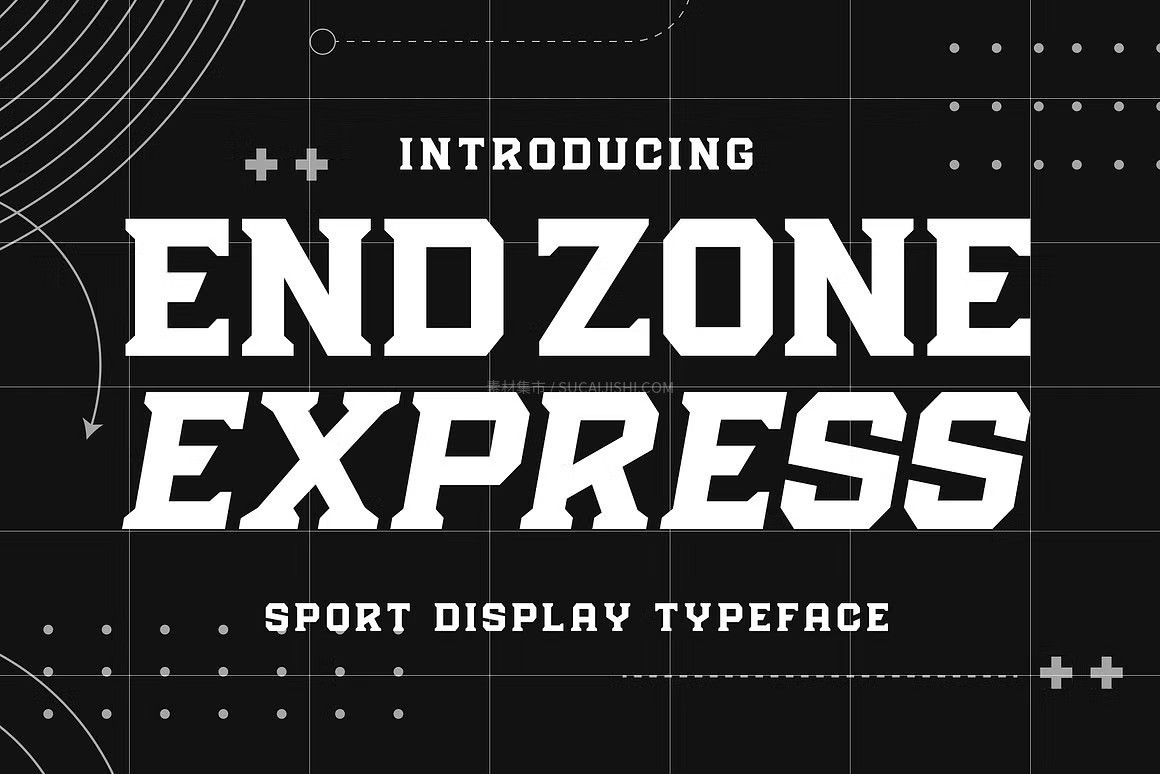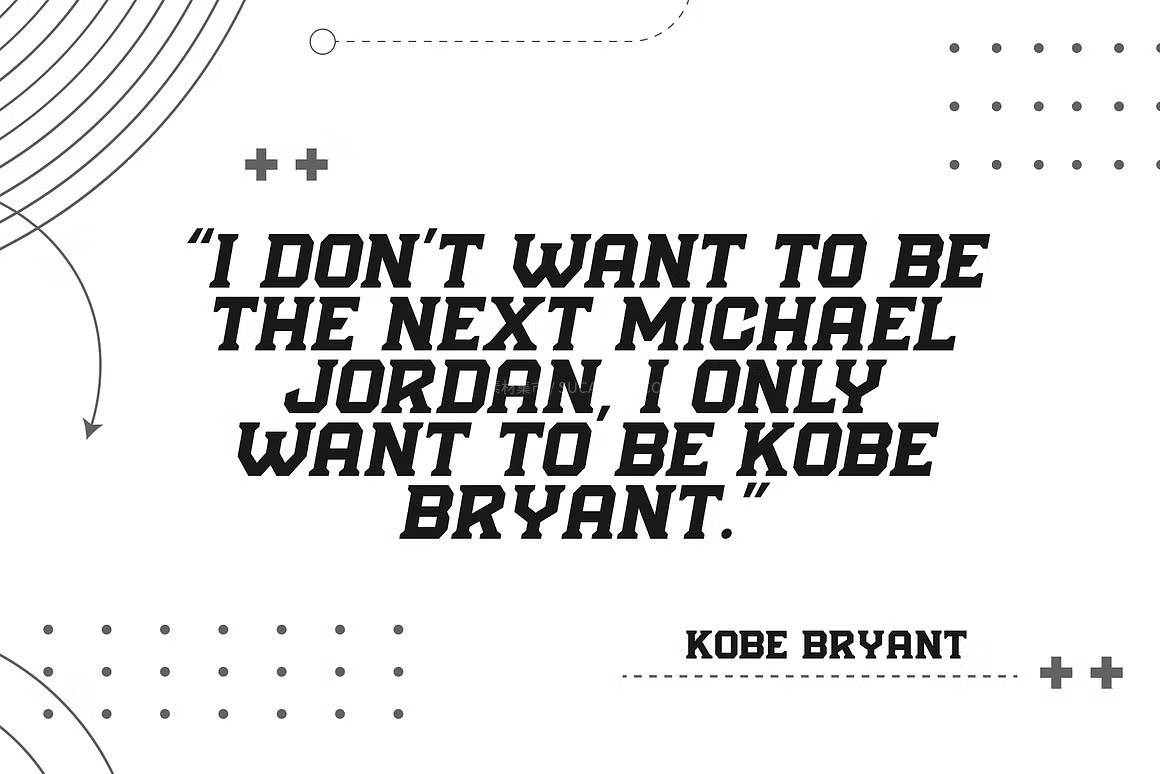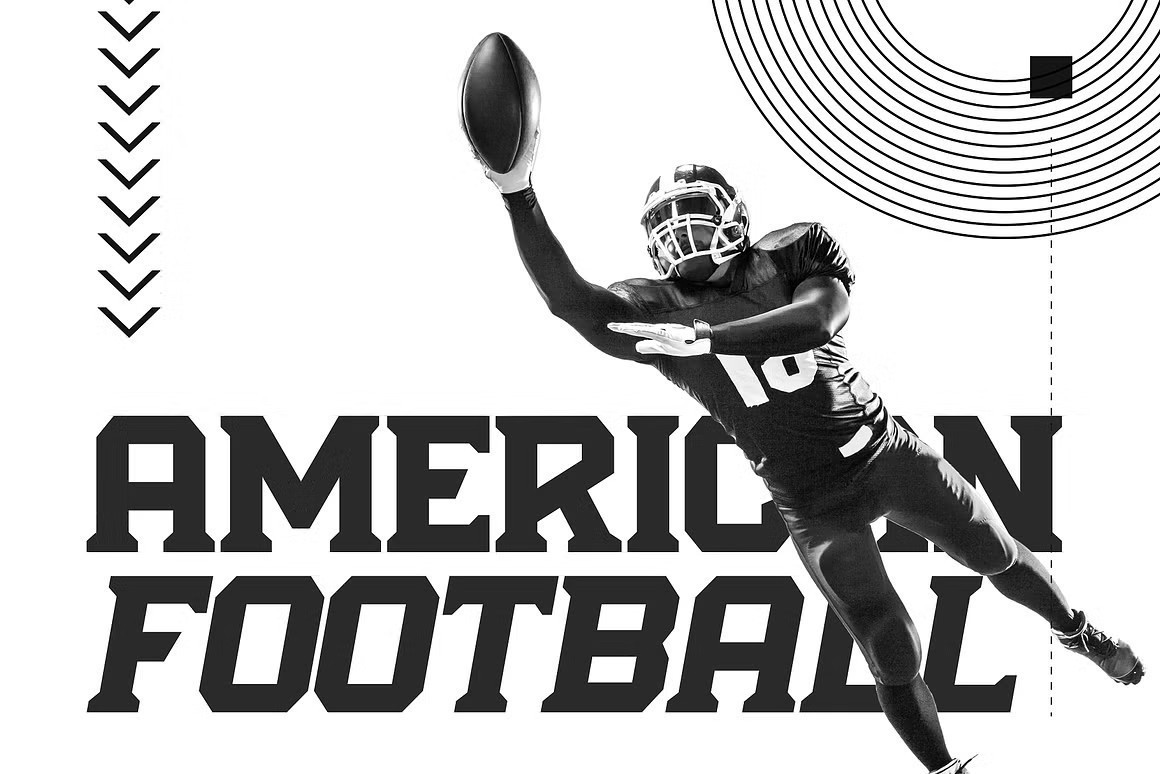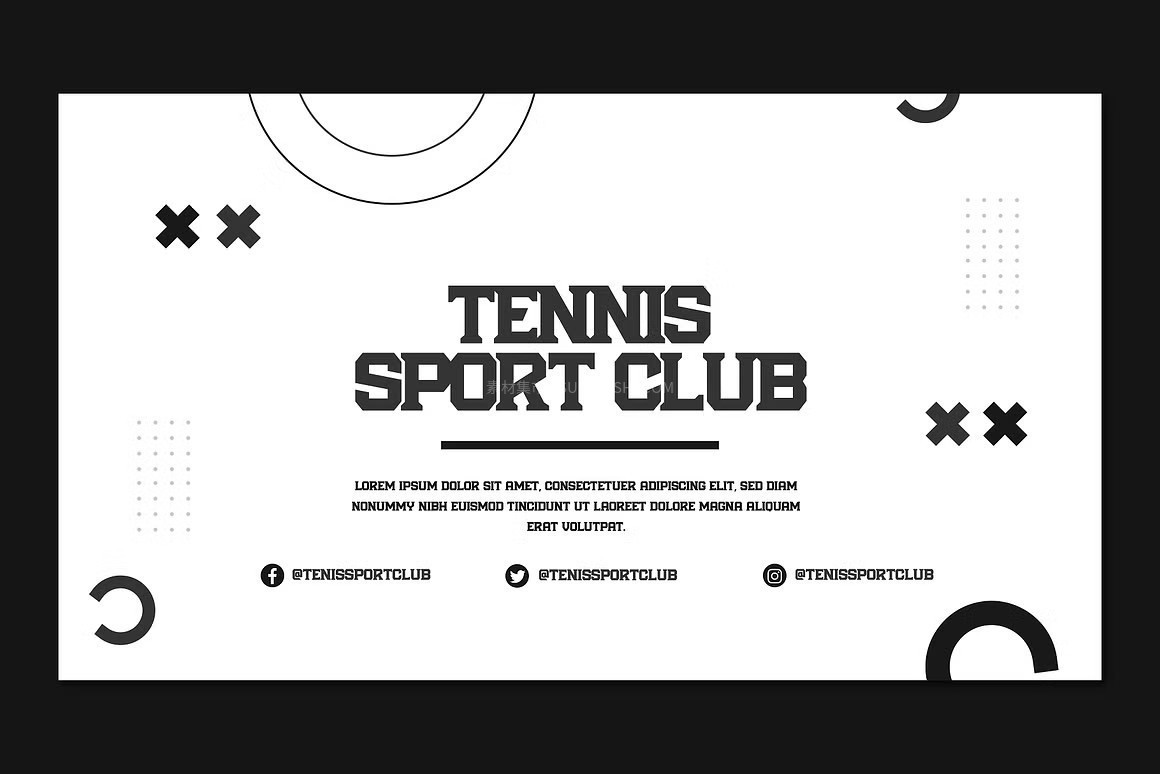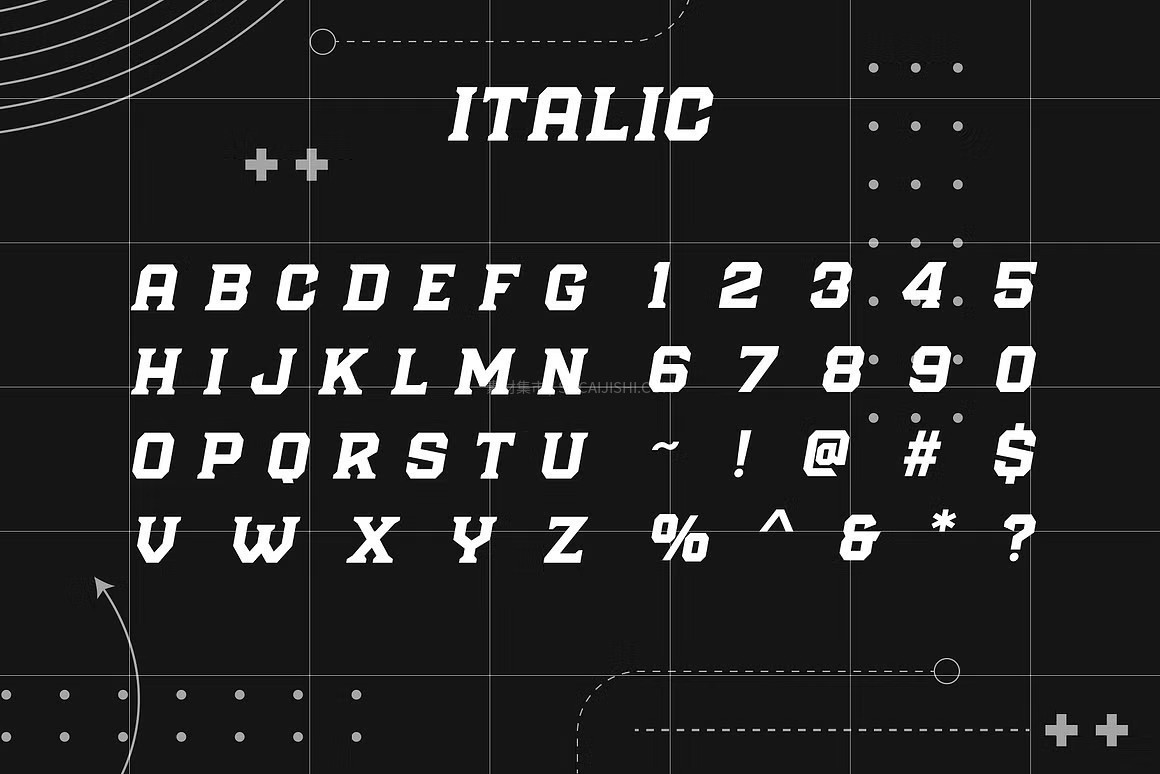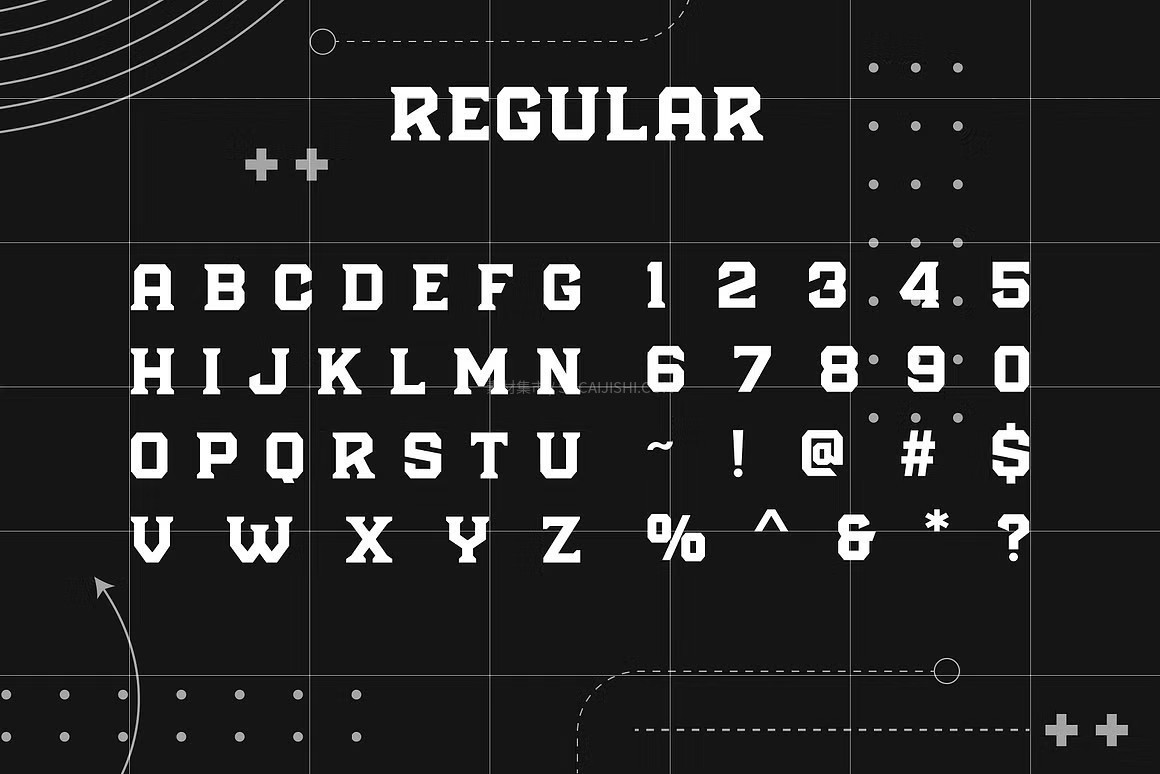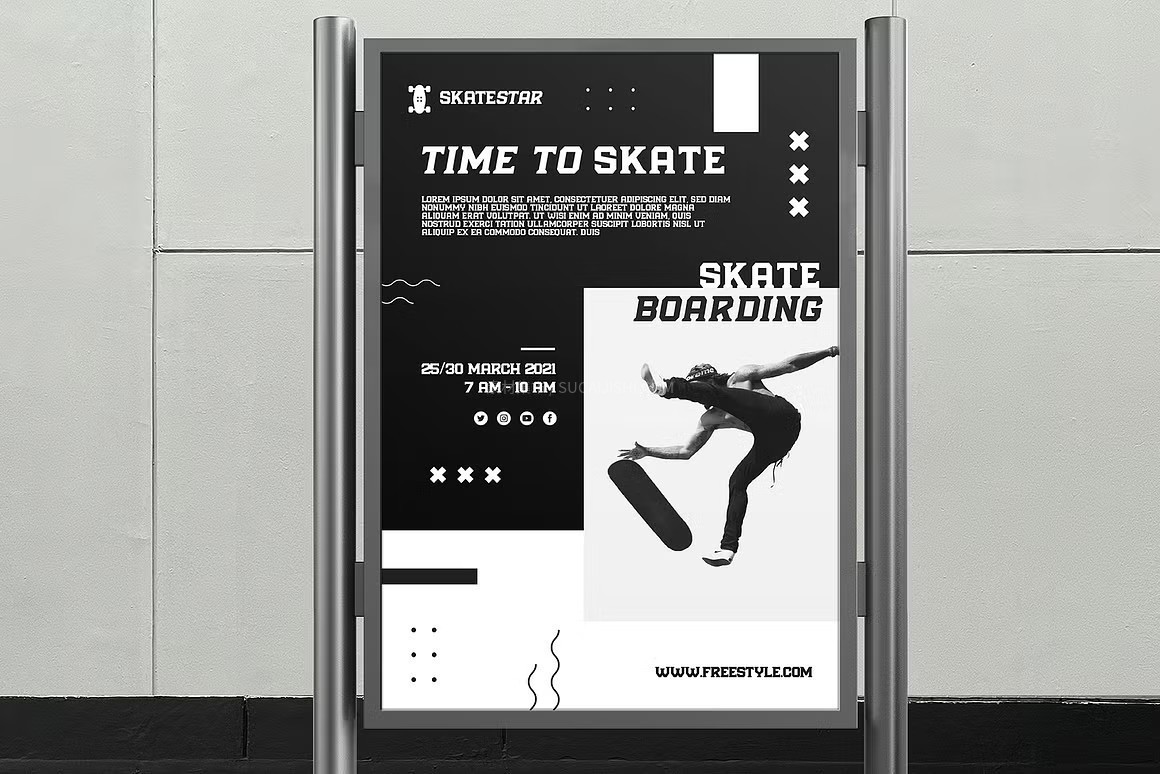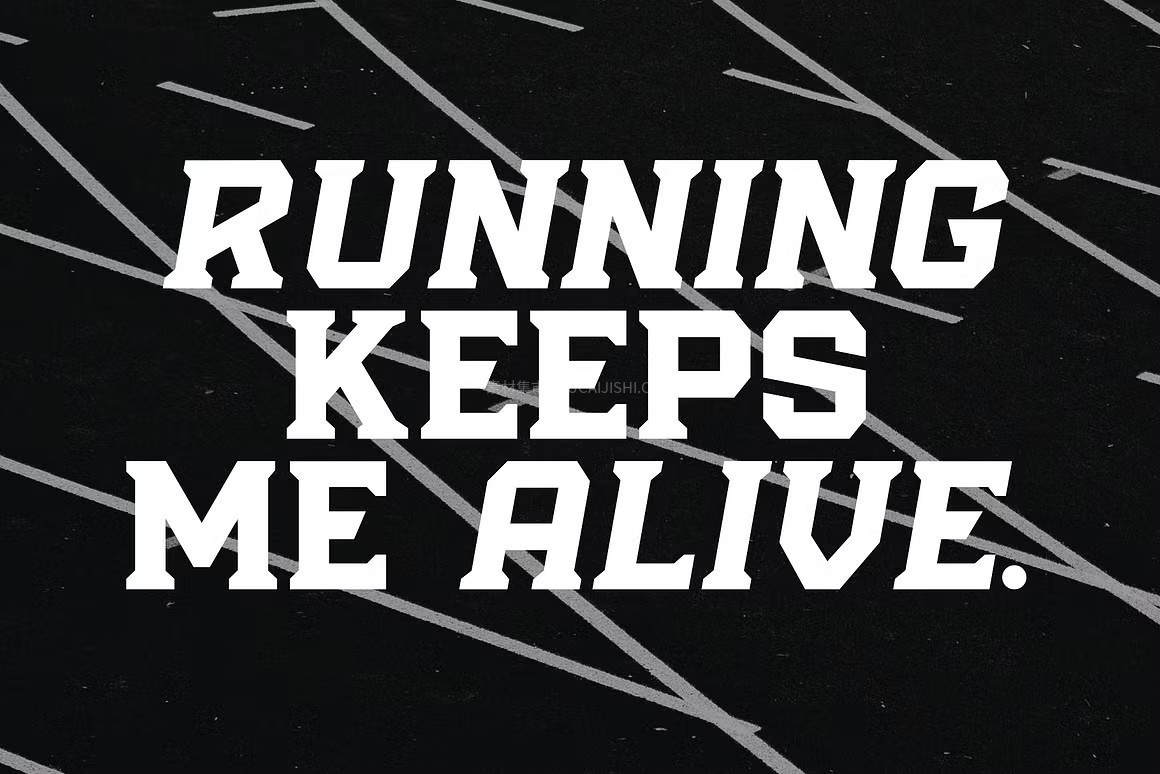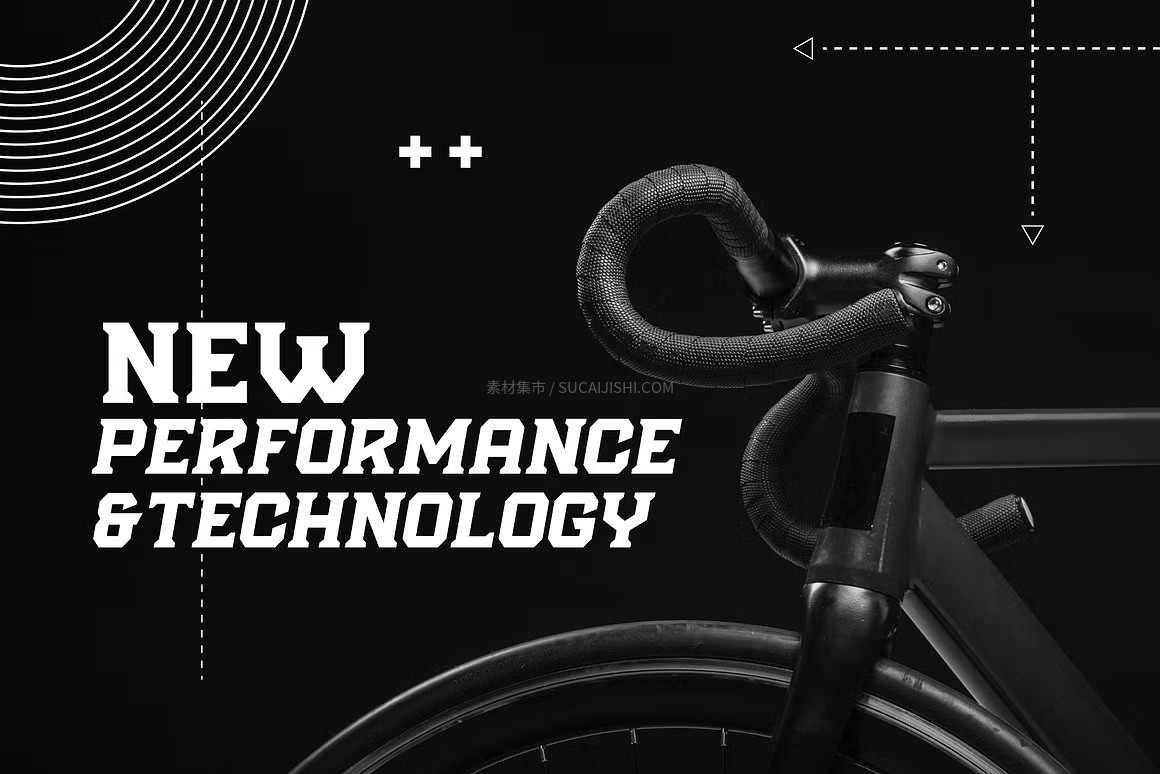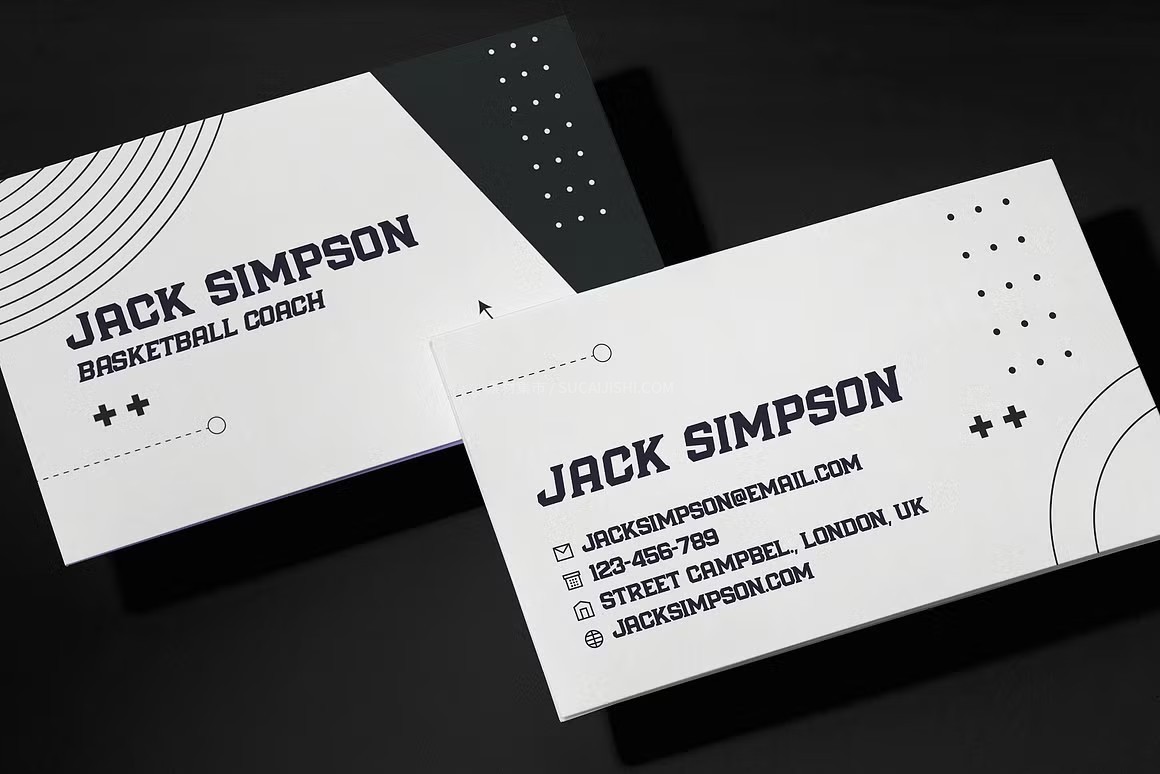
Endzone Express NFL美式橄榄球运动字体
如果你正在寻找一款充满美式摔撞、速度与力量感的排版神器,Endzone Express 绝对是标准答案!这款专为 NFL美式橄榄球 等高对抗竞技运动打造的硬核字体,字形厚重强悍、线条凌厉,自带达阵冲锋(Endzone)的爆发力。它的每一个转折都蕴含着硬朗的工业感与纯粹的肌肉力量,视觉冲击力直接拉满。